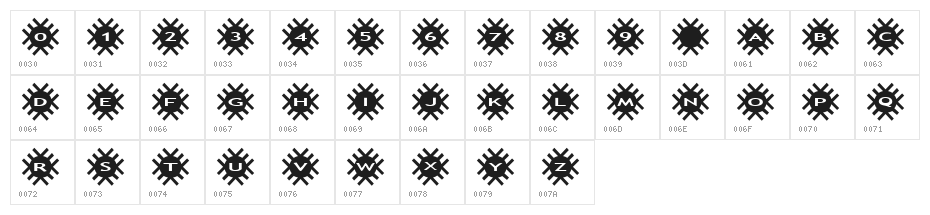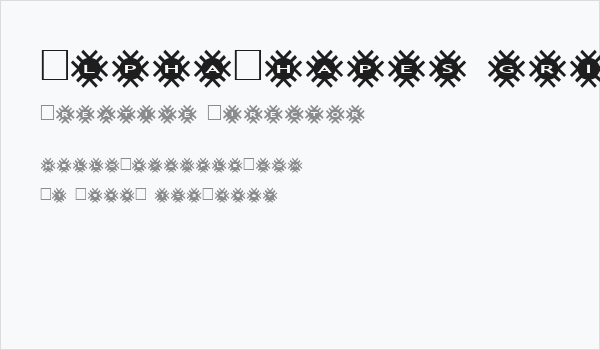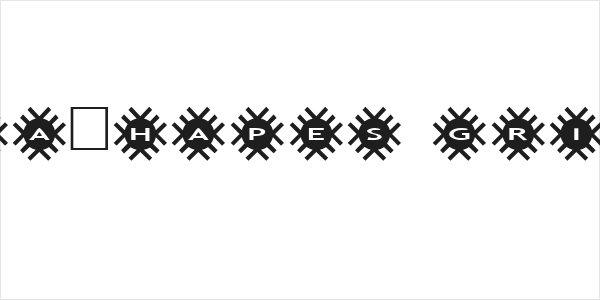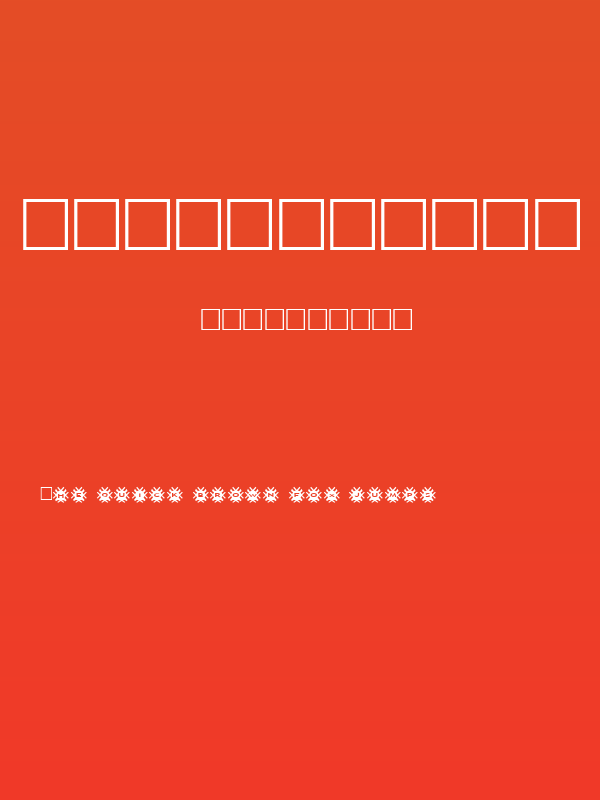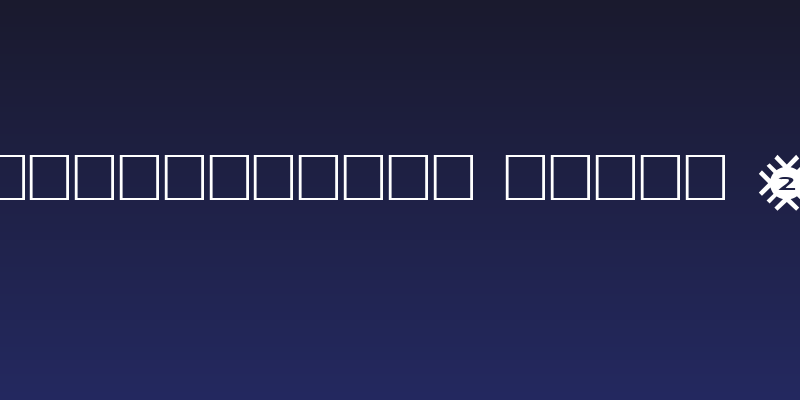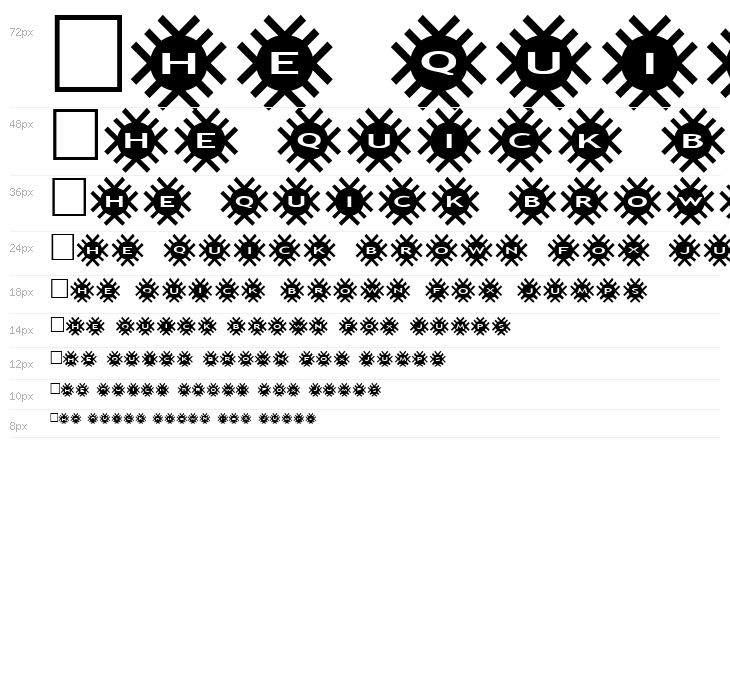
AlphaShapes grids 2 Font
| Stile generale | Modern, Artistic |
| Progetti proposti | Ideal for creative projects such as posters, album covers, or branding materials where a distinctive and artistic look is desired. |